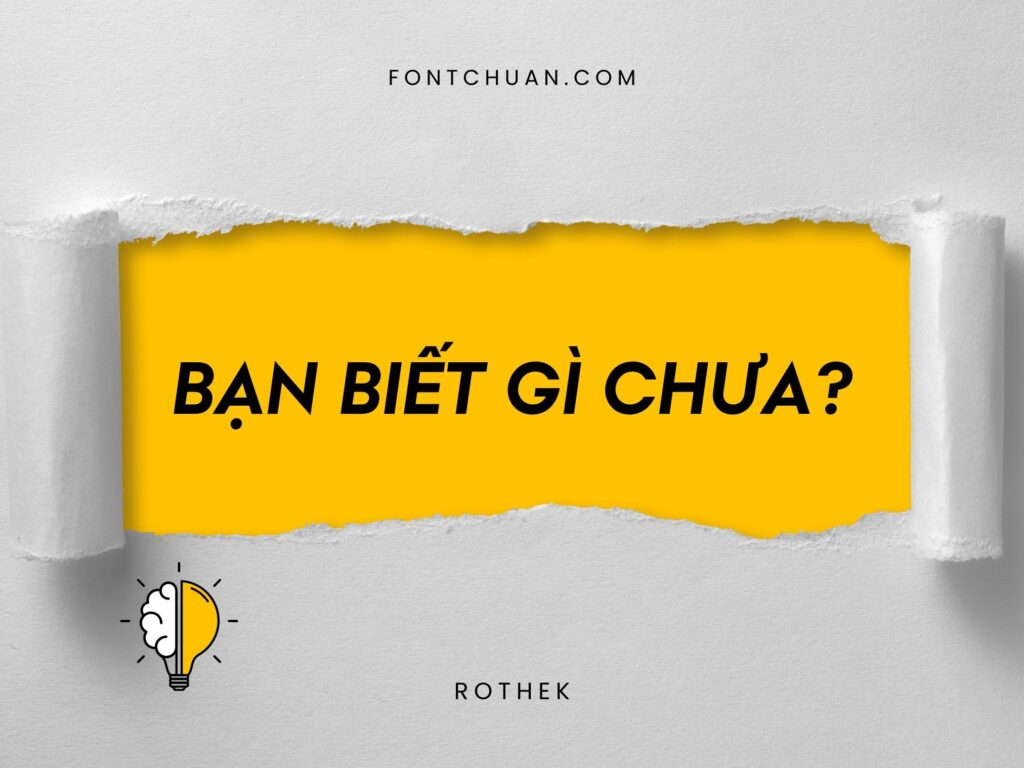
Font Rothek Trọn Bộ Font Tiếng Việt
Rothek là một họ font sans-serif hình học với thiết kế sắc nét, lấy cảm hứng từ phong cách Bauhaus, được thiết kế bởi Evgeny Tantsurin và phát hành bởi Groteskly Yours Studio. Với 22 kiểu chữ tĩnh và 1 font biến đổi, Rothek mang đến sự linh hoạt và hiện đại cho các dự án thiết kế. Nhờ cấu trúc hình học tinh tế cùng tỷ lệ chữ cân đối, Rothek không chỉ được xem là một Font chữ công nghệ lý tưởng cho các sản phẩm kỹ thuật số, ứng dụng và website, mà còn là một Font chữ bất động sản phù hợp để thiết kế logo, biển hiệu hay tài liệu nhận diện thương hiệu trong lĩnh vực nhà đất, mang lại cảm giác chuyên nghiệp và uy tín. Font này hỗ trợ hơn 200 ngôn ngữ, bao gồm cả tiếng Việt, và được sưu tầm và đăng bởi thành viên của Font Chuẩn.
Font có cấu trúc chữ rõ ràng, các đường nét sắc sảo và thiết kế tối giản, tạo nên sự cân bằng giữa tính thẩm mỹ và khả năng đọc. Rothek phù hợp cho các thiết kế liên quan đến thương hiệu, truyền thông xã hội, tiêu đề và nội dung số. Các ngành nghề như quảng cáo, công nghệ, giáo dục và bất động sản có thể tận dụng hiệu quả font này. Ngoài ra, Rothek cũng thích hợp cho các sự kiện như lễ hội, sinh nhật, ngày Nhà giáo và Valentine.